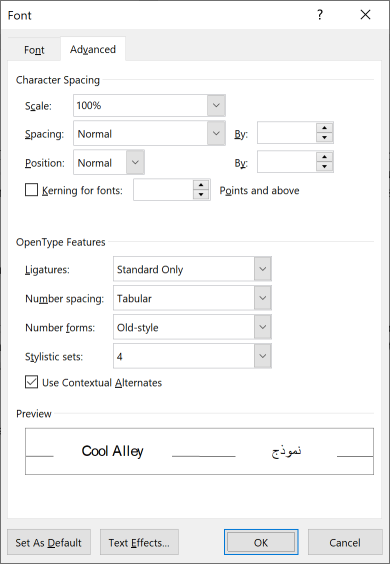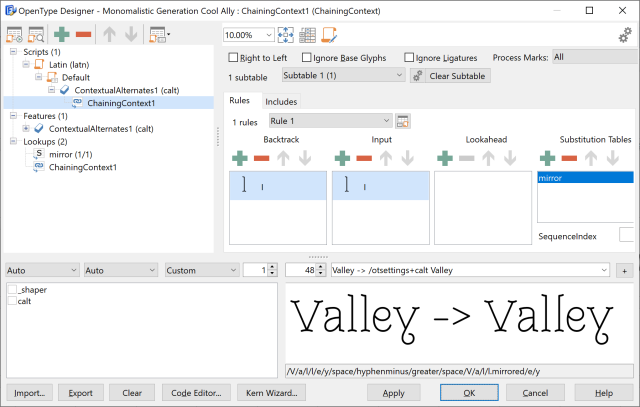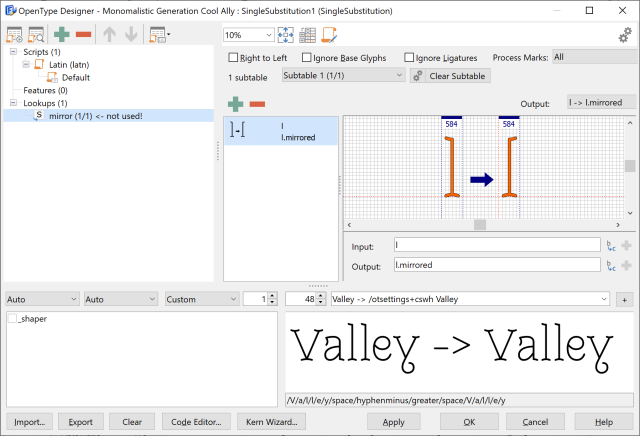
本教程介绍如何为您的字体添加花式连笔(swashes)、连字(ligatures)与风格化集(stylistic sets)等亮点。
本教程不是关于使用字体,而是关于字体设计师如何向字体添加花饰、连字和样式集等宝石。这很容易实现,并且可能会促进您的字体销售。
字体可以远不止是一堆字符。如今,所有专业字体都附带 OpenType 布局功能,我们将解释如何向字体添加几种最常见和最受欢迎的功能:
这些功能都用于用一个替换品替换一个或多个字符。我们将不讨论定位功能,因为这些已经在其他教程中处理了。<TODO 参见间距和字距>。
使用 FontCreator,除了上下文替代之外,所有功能都可以自动添加到字体中。只需确保您添加了额外的字形,并根据我们的 字形命名约定 对其进行命名。
在 OpenType 设计器窗口中,单击左上角的第一个图标以打开生成和更新 OpenType 功能窗口。您现在可以选择要生成和/或更新的功能。
下面我们将为每个功能提供所需字形名称。
将此功能用于使用自定义设计的连字看起来更好的字母组合,例如 fi、fl 和 ffl。通常它们会改善否则会重叠的字母外观。应用程序知道这些连字应在正常条件下使用,但用户可能会禁用 liga 功能。
FontCreator 说明:标准连字会自动检测,因此不必担心这些。如果您想添加额外的连字,请使用连字命名约定,以及 .liga 后缀。如果您想为这三个字符的组合 "f f b" 添加连字,请将其命名为 "f_f_b.liga"。
有 20 个功能可用于样式集,它们都允许对应于字符集部分的样式变体字形集,例如,您可以为开放字母提供封闭的替代品。
FontCreator 说明:给字形原始字符的名称,并为样式集添加相应的后缀。因此,如果您有字母 "g" 的变体,并且希望它在样式集 4 中,请将其命名为 "g.ss04"。
这个很容易添加,因为它只需要一个额外的字形。它允许最终用户用替代形式替换零的默认形式,例如,使用对角斜线穿过计数器来区分 0 和 O(零和大写 O)。
FontCreator 说明:给斜杠零这个名称:"zero.zero"。
我们强烈建议您向字体添加几种数字变体,因为最终用户可能只使用带有替代数字的字体。对于财务和市场研究文档,表格数字最重要,而对于营销手册和广告,旧式数字可能更合适,因为它们的设计看起来更像小写字母。
FontCreator 说明:向所有旧式数字添加 ".onum",例如 "zero.onum",并向所有表格数字添加 ".tnum",例如 "zero.tnum" 等。
此功能允许最终用户用相应的装饰字形替换默认字符。您可以为给定字符提供多个花饰替代品。
FontCreator 说明:向所有装饰字形添加 ".swsh" 后缀。
本教程中的最后一个功能更复杂,因为它允许您添加智能替换,这些替换基于考虑替换的字符之前和/或之后的字符。例如,如果小写字母 l 前面有另一个小写字母 l,您将使其使用替代字形。
FontCreator 说明:它需要两个手动步骤:
1. 添加替换查找(将其命名为 mirror)并添加一项:"l -> l.mirrored"。
2. 向上下文替代功能添加链式上下文替换查找,并向其添加此项:回溯 "l",输入 "l",并向其添加替换表 "mirror"。
使用 FontCreator,很容易向字体添加高级 OpenType 布局功能。
然而,并非所有应用程序都完全支持所有 OpenType 布局功能,因此请测试您的字体,并向客户提供关于他们可以在哪里使用哪些 OpenType 功能的准确信息。
Illustrator、InDesign、CorelDRAW 和 Affinity Designer 支持我们在本教程中展示的所有替换功能。Word 2010 及更高版本几乎支持所有这些功能(尚不支持斜杠零和花饰),可以通过单击格式 → 字体 → 高级来访问: